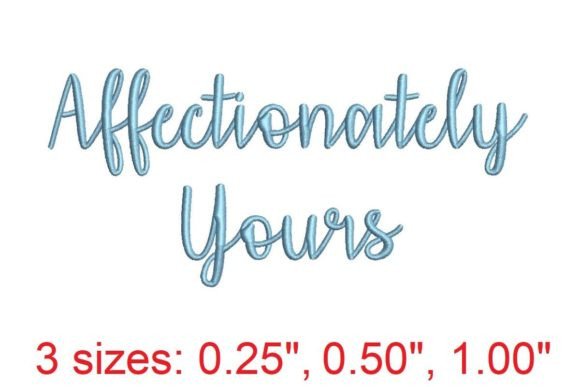
Affectionately Yours Embroidery Font
Znalezienie odpowiednich elementów projektu może być wyzwaniem, ale Affectionately Yours Embroidery Font oferuje wyjątkową kolekcję, która natychmiast ulepszy Twoją pracę.
Niezależnie od tego, czy tworzysz produkty POD (druk na żądanie), zaproszenia ślubne czy grafiki do mediów społecznościowych, Affectionately Yours Embroidery Font będzie idealnym wyborem.